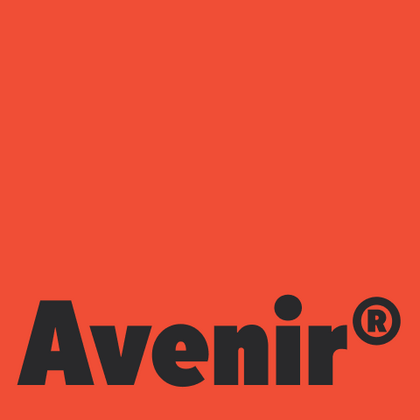
Шрифты похожие на Avenir
Шрифтовая альтернатива: Avenir
TT Norms® Pro — TT Нормс Про
TT Commons™ Pro — TT Коммонс Про
TT Hoves Pro — ТТ Ховс Про
TT Commons™ Classic — TT Коммонс Классик
TT Turns — ТТ Тернс
TT Neoris — ТТ Неорис
TT Fors — ТТ Форс
TT Interphases Pro — ТТ Интерфейзис Про
TT Travels Text — ТТ Травелс Текст
TT Chocolates — ТТ Чоколитс
TT Wellingtons — ТТ Веллингтонс
TT Smalls — ТТ Смоллс
Шрифты похожие на Avenir
Если вам нравится шрифт Avenir®, посмотрите нашу подборку — здесь вы найдете похожие, но более свежие шрифты. Альтернативные шрифты от TypeType красивы и удобны для чтения и подходят для любых проектов: от логотипов до книг. Варианты от нашей студии дают большие возможности. Они сохраняют все плюсы оригинала, но выглядят более современно. В нашей коллекции каждый найдет подходящий шрифт для своих задач — простой и понятный в использовании.
Если вы устали от «заезженных» шрифтов и ищете гарнитуры, похожие на Avenir, ознакомьтесь с нашими лучшими альтернативами Avenir. Это шрифты, которые имеют близкие характеристики, но в то же время обладают новыми уникальными особенностями дизайна. Например, относятся к той же категории шрифтов, подходят для тех же целей и имеют похожие черты, но отличаются в деталях или пропорциях.
Найдите отличную замену Avenir и попытайтесь имитировать похожее настроение, передать нужное вам ощущение, используя его в своих проектах. Каждый шрифт, представленный на этой странице, является двойником шрифта Avenir, фактически его полным аналогом.